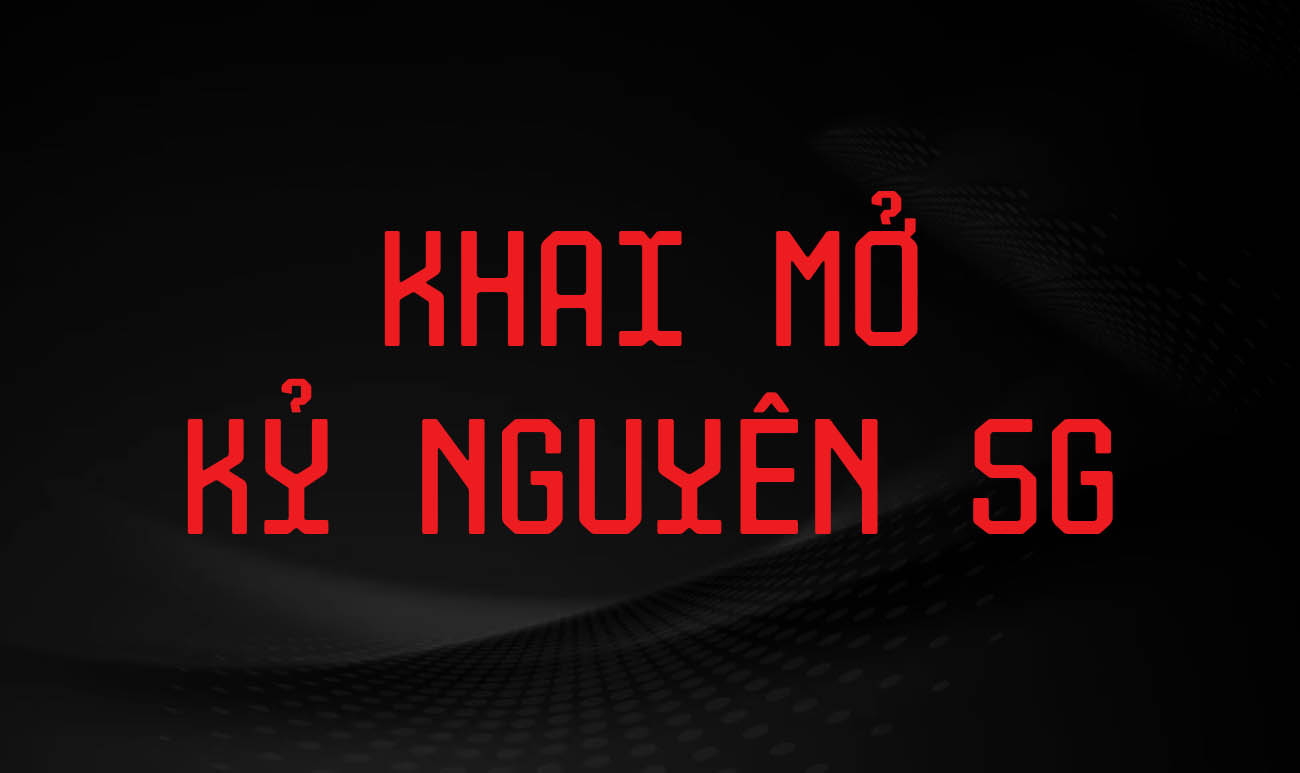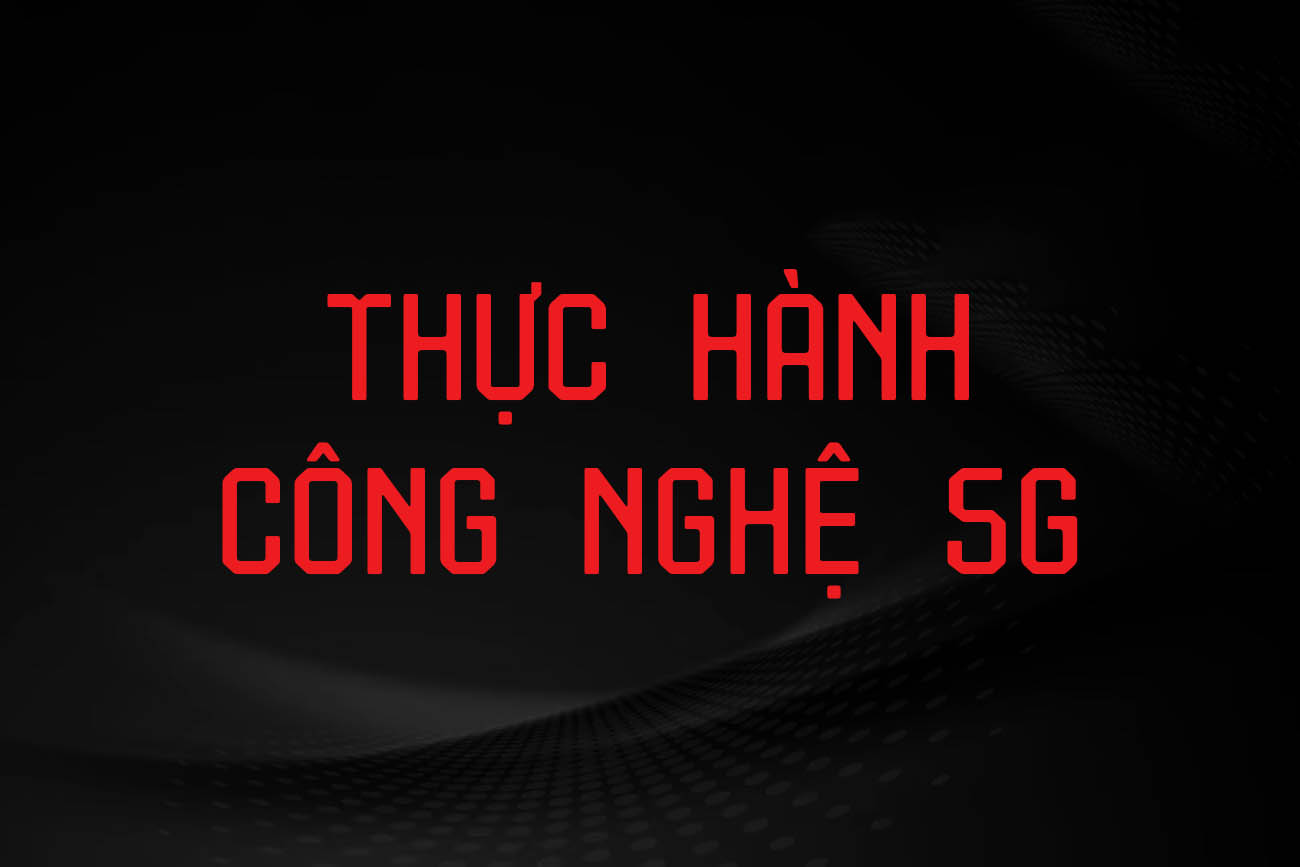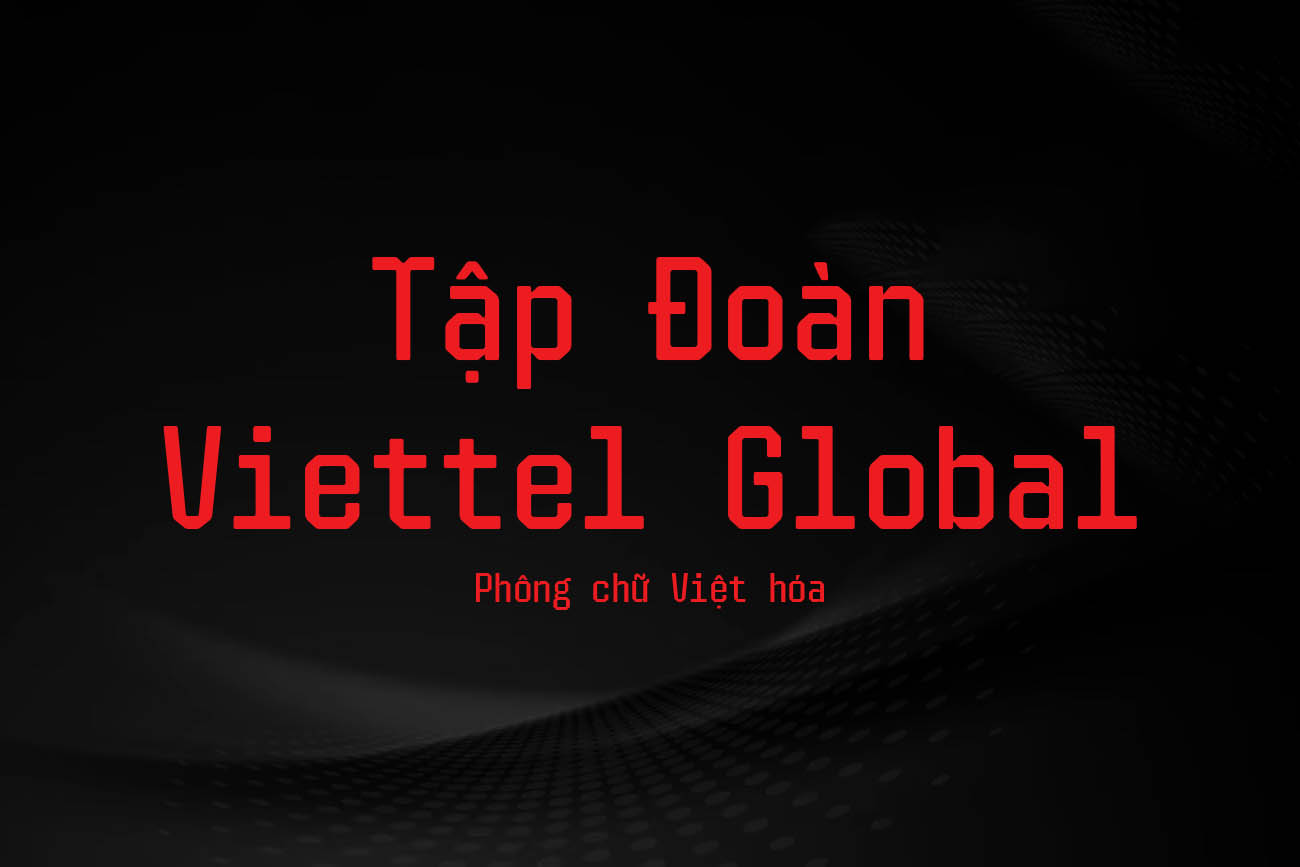
Trong thế giới thiết kế hiện đại, font chữ không chỉ đơn thuần là công cụ truyền tải nội dung – mà còn là linh hồn của thẩm mỹ thị giác. Đặc biệt trong các dự án mang tính công nghệ, kỹ thuật số, AI hay giao diện người dùng (UI), việc lựa chọn một font chữ công nghệ hiện đại và sắc nét là điều không thể thiếu. Và nếu bạn đang tìm kiếm một font chữ Việt hóa mang đậm tinh thần digital, kiểu dáng mạnh mẽ nhưng vẫn dễ sử dụng, thì TH Degrad Mono chắc chắn là lựa chọn đáng cân nhắc.
Giới thiệu nhanh về TH Degrad Mono
TH Degrad Mono là một bộ font chữ công nghệ Việt hóa được thiết kế bởi Holyline Design và Việt hóa bởi Phạm Sơn – một trong những cái tên quen thuộc trong cộng đồng sáng tạo font tiếng Việt. Đây là bộ font được xây dựng theo phong cách mono-space (cách đều) với các chi tiết thiết kế tối giản, sắc nét, nhưng vẫn gợi cảm giác sáng tạo và cá tính.
Vì sao TH Degrad Mono là lựa chọn lý tưởng cho thiết kế công nghệ?
1. Phong cách mono hiện đại, mạnh mẽ
Ngay từ cái nhìn đầu tiên, TH Degrad Mono đã gây ấn tượng bởi các đường nét hình học sắc sảo, đều nhau theo dạng mono – rất phù hợp với thiết kế trong lĩnh vực lập trình, công nghệ AI, dữ liệu lớn, các giao diện UI/UX hoặc branding liên quan đến ngành công nghiệp số.
Kiểu chữ này gợi lên cảm giác tối giản nhưng không đơn điệu, chuyên nghiệp nhưng không cứng nhắc – một phong cách đang rất được ưa chuộng trong các sản phẩm công nghệ cao.
2. Dễ sử dụng với tiếng Việt chuẩn
Điểm mạnh của font chữ Việt hóa TH Degrad Mono nằm ở việc các dấu tiếng Việt được xử lý chỉn chu. Dù bạn sử dụng trên tiêu đề in đậm, đoạn mô tả ngắn hay trong bảng điều khiển số liệu, font vẫn hiển thị sắc nét, rõ ràng và thẩm mỹ. Không còn tình trạng lỗi dấu, tràn dòng, hay mất cân đối khi phối cùng các ngôn ngữ khác.
Nếu bạn cần một font vừa hiện đại, vừa dễ phối kết với các yếu tố đồ họa như icon, shape, hoặc các hình ảnh công nghệ, thì TH Degrad Mono là sự lựa chọn cực kỳ tối ưu.
Tổng kết
Trong bối cảnh ngành công nghệ ngày càng phát triển, thiết kế hiện đại đòi hỏi những font chữ sắc sảo, linh hoạt và chuẩn tiếng Việt. TH Degrad Mono không chỉ đáp ứng các yêu cầu kỹ thuật mà còn giúp bạn thể hiện phong cách thiết kế đậm chất công nghệ, tối giản nhưng khác biệt.
Nếu bạn đang tìm kiếm một font chữ công nghệ Việt hóa có chất lượng cao, dễ sử dụng, thân thiện với người dùng và thể hiện tốt tinh thần đổi mới – thì TH Degrad Mono là một lựa chọn không thể bỏ qua.